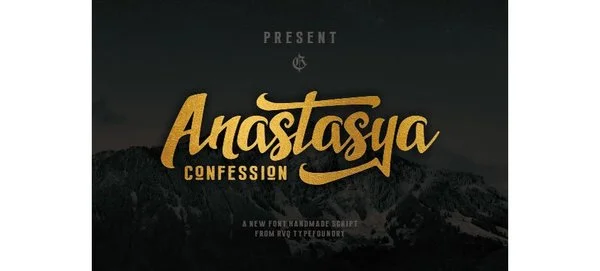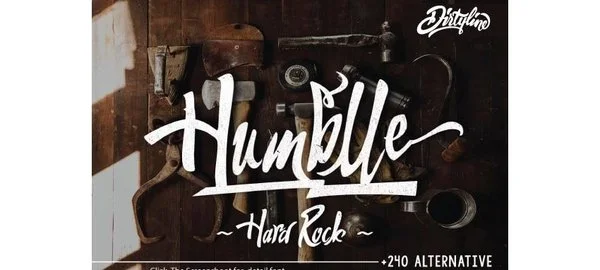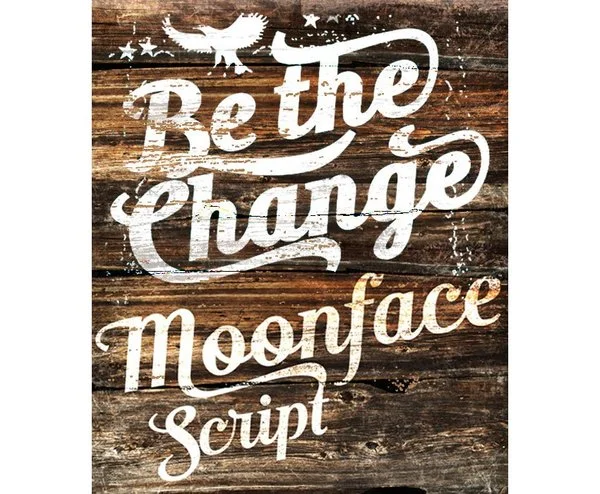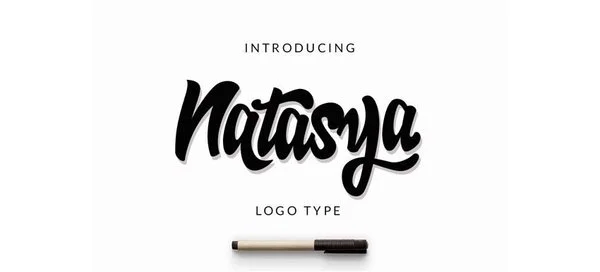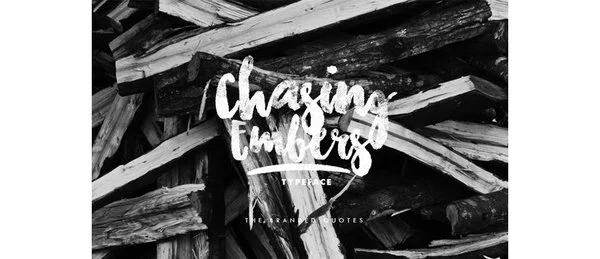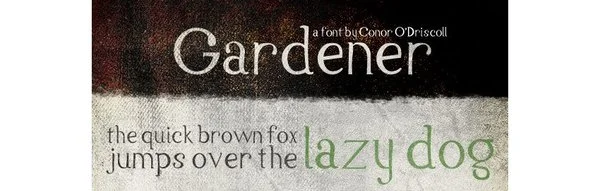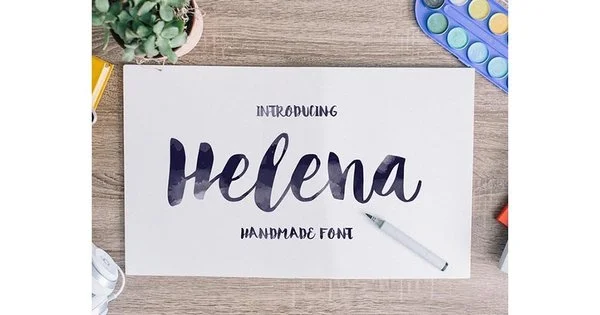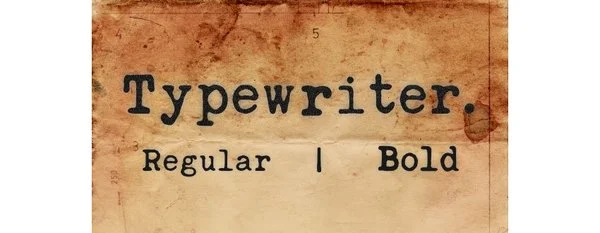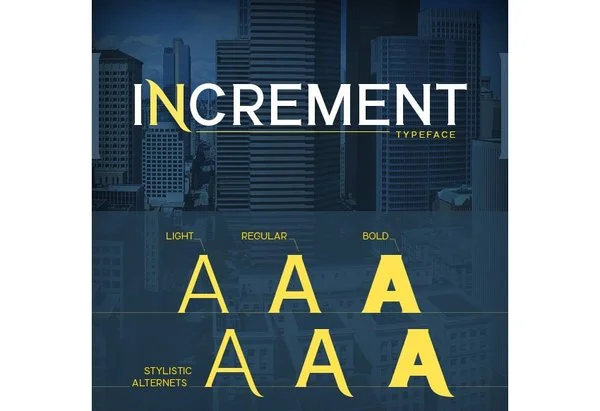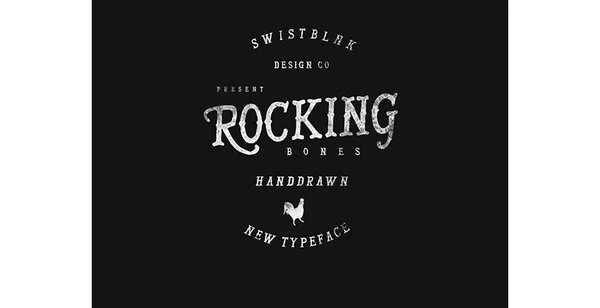
Nhiều designer thích sử dụng những font chữ thú vị, độc đáo để thể hiện cá tính của mình trong mỗi tác phẩm hay trong công việc. Tuy nhiên, có một điểm chung là danh sách font chữ của họ luôn có từ kiểu Serif cho đến Script và nhiều hơn nữa những font chữ phải có cho các designer chuyên nghiệp. Vì vậy, bài viết này Printgo sẽ giới thiệu đến các bạn tổng hợp các font chữ đẹp cho designer và link tổng hợp các font chữ đẹp cho thiết kế ở cuối bài để các bạn tải về miễn phí.
Serif là font chữ đẹp cho thiết kế, tuyệt vời cho tất cả các nhu cầu design chuyên nghiệp và cá tính. Font chữ này có tác động tích cực đến thương hiệu công ty, truyền thông in ấn, và một loạt các nhu cầu phông chữ khác. Serif đặc biệt phù hợp cho các logo kiểu cách. Các font chữ Serif thường được sử dụng bao gồm:
Font chữ này là sự kết hợp giữa kết cấu tự nhiên với độ cứng của kiểu Serif. Các designer thường sử dụng font chữ này để thêm tạo điểm nhấn kiểu homemade cho các thiết kế bao bì hoặc in ấn cần cảm giác hữu cơ, nuôi trồng tại nhà.
Font chữ này rất tuyệt vời khi bạn cần một thiết kế với kiểu cách giống máy đánh chữ cổ. Bạn có thể thể hiện chi tiết trong các mẫu chữ không đồng nhất mà một máy đánh chữ thực sự sẽ tạo ra.
Phông chữ này bao gồm hai bộ phong cách: một loại thì hơi kiểu serif và loại kia thì có các nét cong ấn tượng. Chúng trộn lẫn với nhau tạo cho văn bản một diện mạo kiểu cách và vô cùng ấn tượng
Đây là một font chữ serif mang phong cách vintage rất phù hợp cho các logo và thiết kế in ấn (đặc biệt là quần áo). Với phong cách in tay xen kẽ và tặng thêm một số vectơ, phông chữ này cung cấp cho bạn mọi thứ mà một designer cần để tạo ra những thiết kế cổ điển tuyệt vời.
Font chữ serif lấy cảm hứng từ thời trang này là một sự bổ sung tuyệt vời cho bất kỳ bộ sưu tập font chữ nào tập trung vào việc tạo ra các tiêu đề hoặc thiết kế in ấn sáng tạo. Sự pha trộn giữa các nét dày và mảnh chắc chắn sẽ tạo nên một bộ những glyph xuất sắc.
Đây là một font chữ kiểu cọ viết tay. Font chữ này sẽ tuyệt vời khi đi cùng với kết cấu màu nước hay màu mực, cho phép người dùng bắt chước một phong cách handmade thực sự.
Font Script là font chữ có cấu trúc mảnh và được làm nổi bật bởi các đường cong như hình vẽ. Một vài font Script đẹp thường được dùng trong thiết kế:
Đây là một kiểu chữ viết script bằng cọ bóng bẩy mà rất hiệu quả trong thiết kế bộ nhận diện thương hiệu, nội dung truyền thông xã hội, và nhiều hơn nữa.
Các chữ cái của Humble Script như đang nhảy nhót trên bất kỳ các trang, màn hình hoặc nội dung nào mà bạn tạo ra. Nó hoàn hảo cho các tài liệu tiếp thị hoặc các mẫu logo, kiểu script này tạo cho ta cảm giác ngộ nghĩ và đáng yêu.
Moonface Script là một lựa chọn tuyệt vời cho các font chữ script theo kiểu bóng chày và thể thao.
Những font chữ script này tròn, lớn và là một lựa chọn không thể thiếu với bất cứ một nhà thiết kế nào.
Những font chữ dạng vẽ cọ khô là một sự bổ sung tuyệt vời cho bộ sưu tập của bạn dành cho các thiết kế tiếp thị và thiết kế in ấn. Akula là một ví dụ điển hình cho phong cách đó.